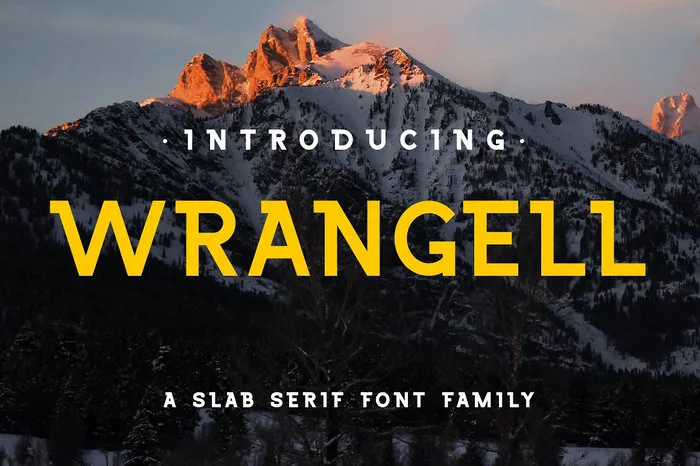
Wrangell Typeface – Fonte Grátis
Wrangell Typeface
Introduzimos a família Wrangell! Desenhada por Paul van Oijen, ela é uma mistura contemporânea e natural de uma família de fontes Slab Serif, oferecendo um twist moderno para visuais clássicos. A Wrangell não apenas funciona perfeitamente sozinha, mas também se encaixa perfeitamente como fonte secundária para seu logotipo ou marca já existente. Seu estilo atemporal e elegante o tornam uma opção ideal tanto para títulos de capa quanto para headlines. A Wrangell é certamente um recurso valioso para quem busca manter a estética clássica, mas sem perder aquela sensação moderna. E que tal se você experimentar adicionar a sua marca com essa fonte? Sua identidade visual será mais forte e impactante como resultado.